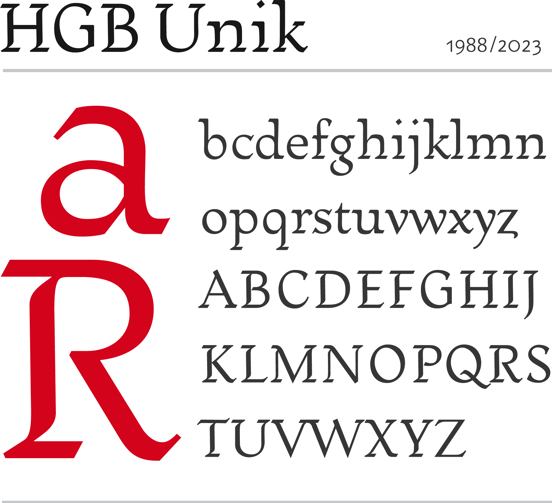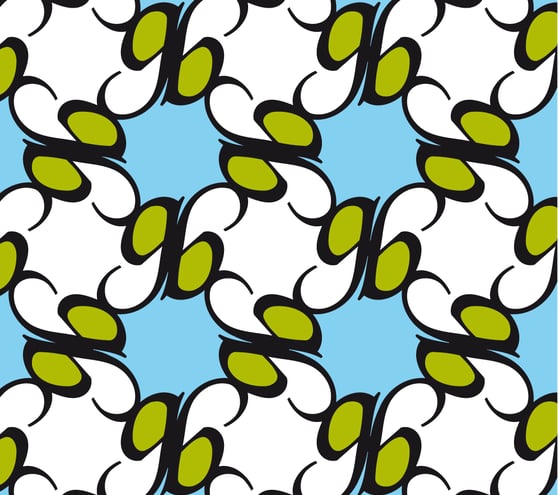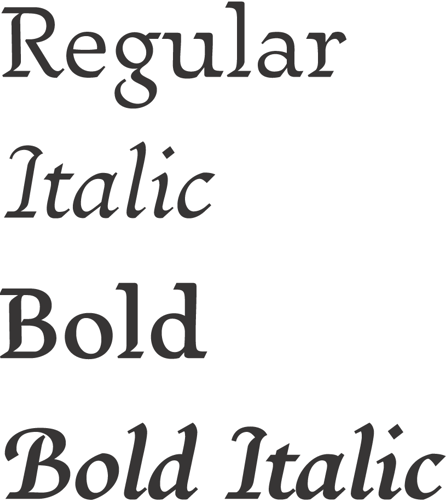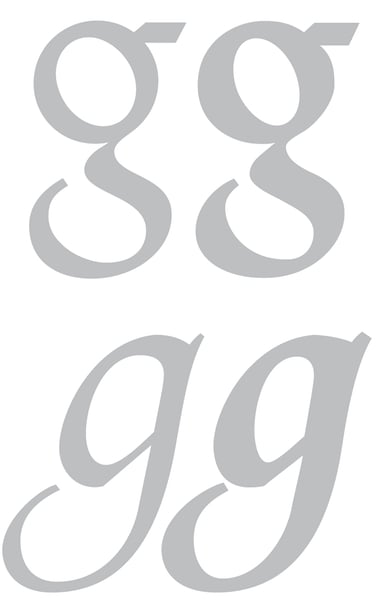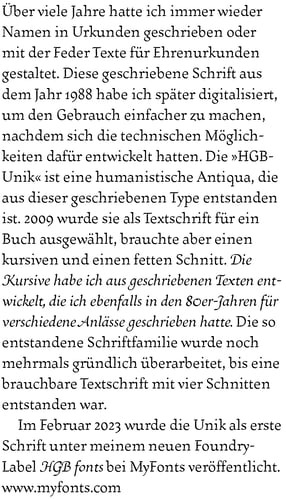
HGB Unik
Über viele Jahre hatte ich immer wieder Namen in Urkunden geschrieben oder mit der Feder Texte für Ehrenurkunden gestaltet. Diese geschriebene Schrift aus dem Jahr 1988 habe ich später digitalisiert, um den Gebrauch einfacher zu machen, nachdem sich die technischen Möglichkeiten dafür entwickelt hatten. Die »HGB-Unik« ist eine humanistische, handschriftliche Antiqua, die aus dieser geschriebenen Type entstanden ist. 2009 wurde sie als Textschrift für ein Buch ausgewählt, brauchte aber einen kursiven und einen fetten Schnitt. Die Kursive habe ich aus geschriebenen Texten entwickelt, die ich ebenfalls in den 80er-Jahren für verschiedene Anlässe geschrieben hatte. Die so entstandene Schriftfamilie wurde noch mehrmals gründlich überarbeitet, bis eine brauchbare Textschrift mit vier Schnitten entstanden war. Im Februar 2023 wurde die Unik als erste Schrift unter meinem neuen Foundry-Label HGB fonts bei MyFonts veröffentlicht.